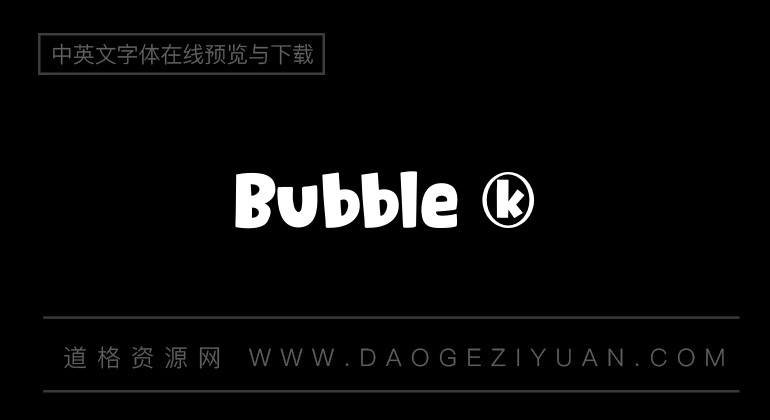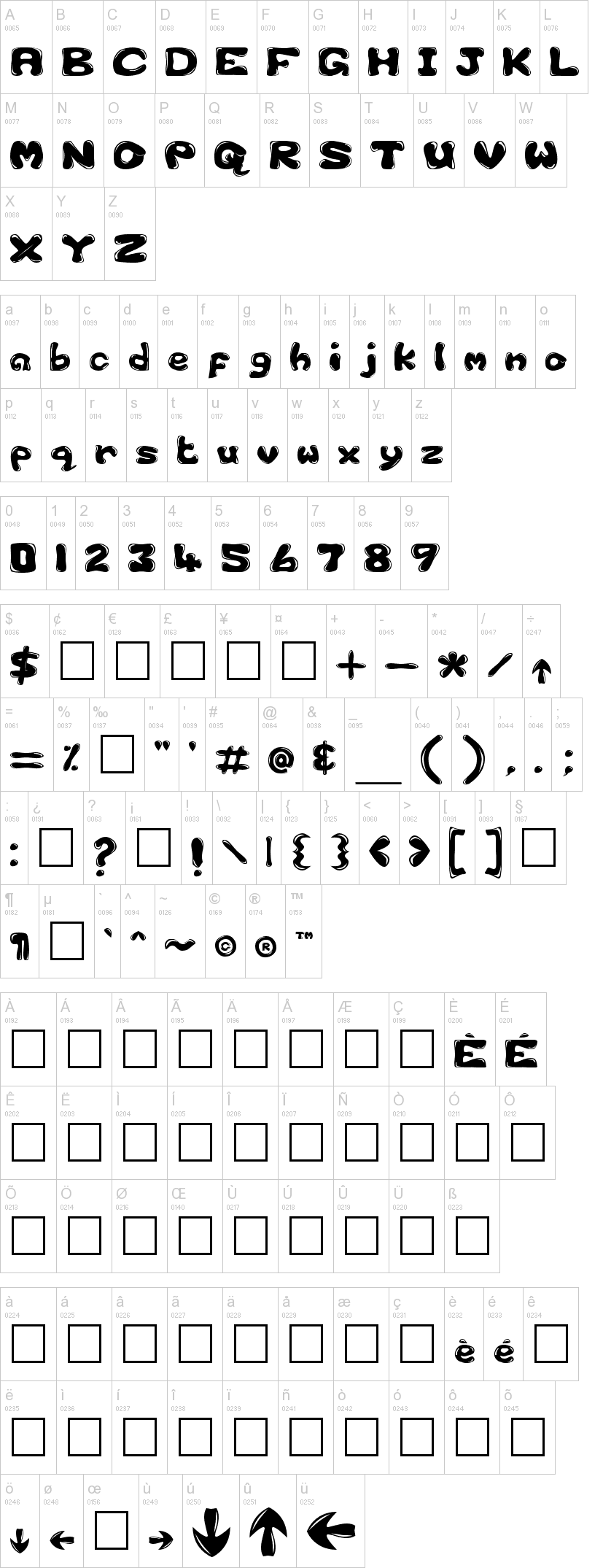
Bubble 1
Bubble 1 是一种漫画风格的字体,字母呈现出充满弹性的气泡状形态,看起来轻松、活泼、幽默。这种字体最初是用于漫画书的文本,但现在也被广泛用于广告、海报、宣传单和其他视觉设计作品中。 Bubble 1 字体的特点是每个字母都被包裹在一个无规则的气泡中,这些气泡的大小和形状各异,但整体呈现出一种亲和力极强的视觉效果。这种字体通常用于表达轻松、有趣的情绪,比如在卡通和漫画中经常使用。 Bubble 1 字体有许多变体,包括粗体和斜体等。它也可以与其他字体、颜色和图像进行组合,以创造出独特的视觉效果。
Bubble 1是一款非常不错的手写艺术字体,具有很好的视觉感,适合于文化类的宣传设计、商业类品牌的广告和产品包装设计以及个性化文字排版等较多场景。